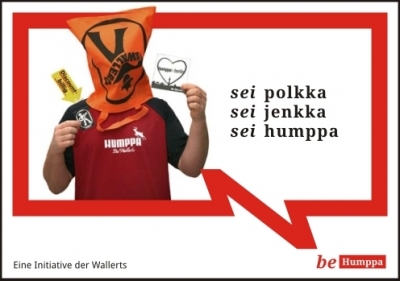
Je größer die Bühne einer Berliner Veranstaltung, und je mehr sich die Politik einmischt (Banken, Love Parade, Tempodrom, Spreedreieck) umso größer das Skandalpotenzial. Die Be-Berlin-Kampagne ist davon nicht ausgenommen.
Im Oktober 2007 haben Andrea Horn (26) und Marc Arroyo (25) an der Ausschreibung der Stadt Berlin teilgenommen. Ihr Slogan »just be.rlin« soll die Vielfältigkeit, Internationalität, Weltoffenheit und Besonderheit Berlins kommunizieren. Sie glauben nun, das die finale Kampagne ihre Grundidee – honorarfrei – verwendet und erläutern dies in einem eigenen Weblog: justberlin.
womit wir im falle eines pitches bei einem sehr realem problem angelangt sind. wie verhindert man, dass genau das passiert, was hier geschehen zu sein scheint.
unser prof sagte ja immer, dass er bei wettbewerbsteilnahmen einen brief beilegte, dass im falle der unmöglichkeit einer zurücksendung alle beiträge und entwürfe zu vernichten seien und keinesfalls verwendung in irgendeiner form zu finden hätten.
Nur mal so: Calvin Klein warb Mitte der Neunziger mit »Be good. Be bad. Just be.«
Abgesehen davon, dass die Justberlin-Kampagne unglaublich schwach gestaltet ist (Helvetica. Wie unglaublich besonders) weiß ich noch nicht so genau was von der Sache zu halten ist.
Ich muss nochmal nachtreten.
Klar ist es nur ein Layout, aber das möchte man doch verkaufen. Ein Layout muss nun nicht bis ins kleinste Detail durchgeplant und vermaßt sein, aber zumindest gut aussehen sollte es. Da knallt ihr eine Helvetica in Caps mit viel zu enger Spationierung auf belanglose Stockbilder und wundert euch, dass die die (nette, aber nicht wirklich aufregende) Idee klauen und die Gestaltung von Leuten machen lassen, die es wirklich können.
Mein Vorschlag wenn wirklich geklaut wurde: Berlin zahlt an die Freelancer eine vernünftige Aufwandsentschädigung für die Kampagnenidee und nimmt ihnen das Versprechen ab, sich nie wieder mit Gestaltungsabsichten in die Nähe eines Rechners zu begeben.
pravjat: es geht ja in erster linie um den inhalt. die gestaltung steht doch gar nicht zu debatte.
sollte es kein plagiat sein, so wird es sich um einen fall von einfallslosigkeit auf breiter linie handeln. generische ideen sind halt das erste, was man auf die »no go« liste setzen sollte.
nachtreten? kannst du es besser? das ist wirklich der zweite völlig unsinnige kommentar in kurzer zeit.
Entschuldige, ich bin der Meinung, dass Gestaltung immer zur Debatte steht.
in diesem fall gehts um die idee. das ist glaube ich offensichtlich.
um welche idee geht es hier? inhaltlich ist es doch was anderes. und wenn man ein slogan mit einem logo darstellen soll, dann wird es immer ähnlichkeiten haben.
das grundlegende konzept der kampagne auf der webseite ist sehr viel besser als das der realisierten. »just be« geht aber als slogan nicht, auch nicht mit »rlin« hinten dran. einfach ein plagiat.
Ich finde formal wie inhaltlich, die Just Be.rlin Kampagne gelungener, auch wenn ich das Rechteck für Berlin unten, wohl eher in einem Block mit rlin ausgerichtet hätte (und ich wohl eher nicht bei der Helvetica gelandet wäre). Allerdings hat mich Just Be dann doch wieder voll an Kevin Cline erinnert, und die Kampagne ist mir noch zu präsent, als dass ich mich dafür entscheiden könnte.
so far so good • Be: http://www.kraftfoods.at/kraft/images/atde1/pictures/BeLogo_184.gif
Hat die Jury nicht ganz am Anfang gesagt, es wären gleich mehrere Agenturen auf die Idee mit „be Berlin“ gekommen?
Keine Ahnung aber, ob man damit eben „Be.rlin“ gemeint hat.
Dieser Schwachsinn. Der Berliner Senat hatte gleich von Anfang an gesagt, dass der Claim BE BERLIN von sage und schreibe 4 Agenturen eingereicht wurde. Und fairer Weise haben sich auch alle 4 das Preisgeld teilen dürfen. Eine dieser Agenturen hatte auch die Idee mit dem Sei…Sei…Sei… (laut W&V). Wo ist da was geklaut?
Dass so viele Agenturen auf die gleichen Ideen kommen, ist eher kritikwürdig! Übrigens bei Just BErlin und I AMsterdam wäre ich nicht so selbstbewusst und würde mit Vorwürfen um mich werfen!
Och, das Gejammere der schrecklichen Be.rliner nervt aber. Ich werf mal ein Wort in den Ring: Schöpfungshöhe. Peinlich, peinlich.
Be.Berlin mag nicht so dolle sein, aber warum springen alle auf die krude “Plagiat”-Story an?
Beide Kampagnen sind schwach. Falls das wirklich ein Plagiat sein soll sollte Berlin von Andrea und Marc Schadensersatz einfordern… ;)
hallo an alle. was man nicht vergessen sollte ist, dass die just be.rlin Kampagne in sehr kurzer zeit und als layout eingereicht wurde und nicht als fertige kampagne. das was ich jetzt als neue kampagne der stadt berlin sehe finde ich gestalterisch nicht überragend. da haben 6 agenturen 5 monate dran gearbeitet.
Die Profilneurosen mancher Designer sind echt sonderbar. Ganze 4 Designagenturen haben den gleichen Ansatz und gewinnen mehr oder weniger gemeinsam. Und jetzt meldet jemand seinen alleinigen Anspruch an der Idee, welche im Kern zwar Parallelen aufweist, aber noch lange kein Plagiat darstellt – zudem mit einem Claim, welcher unmittelbar mit einem anderen Produkt in Verbindung gebracht wird. Äußerst grotesk!
http://www.bebirmingham.org.uk
Was lernen wir daraus ? Besser recherchieren und
keine Steuergelder für Ideenklau und Recycling verbrennen
bzw. nicht auch noch stolz wie Bolle auf Kopiertes und Banales
durch die Stadtmarketingwelt ziehen !
Du bist Berlin – Du bist Deutschland !
bi birmingham
Dem Calvin-Klein Comment oben kann ich mich nur anschleßen. Just copy.